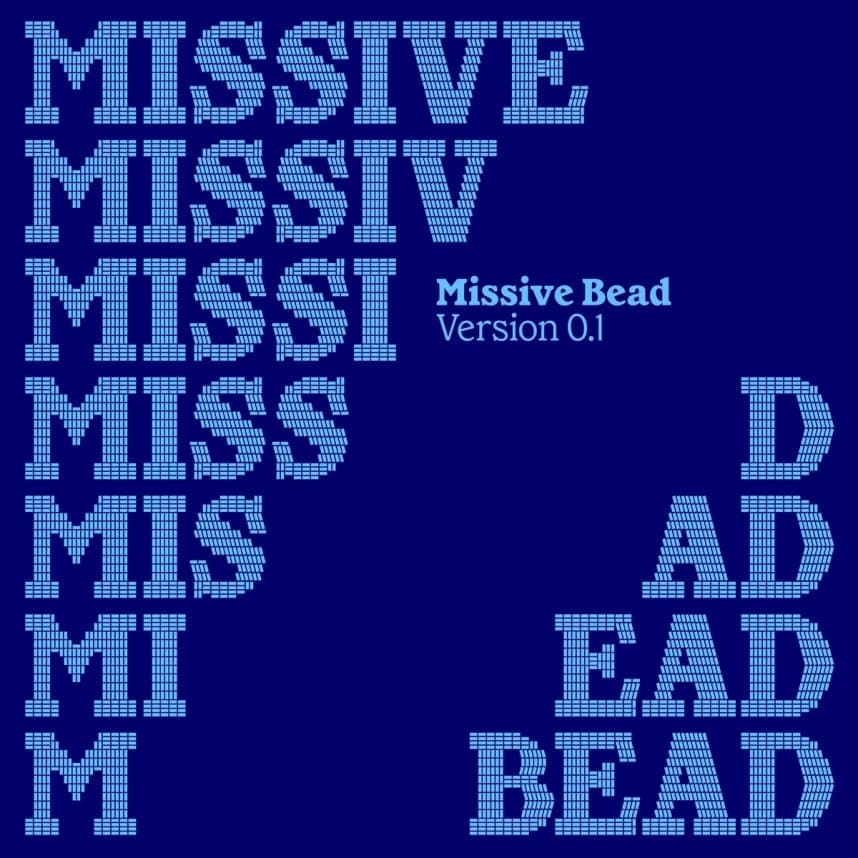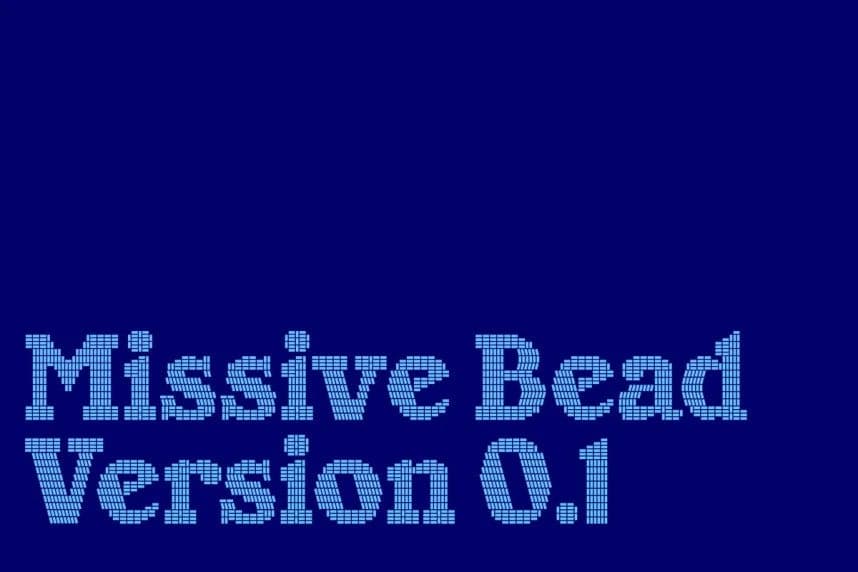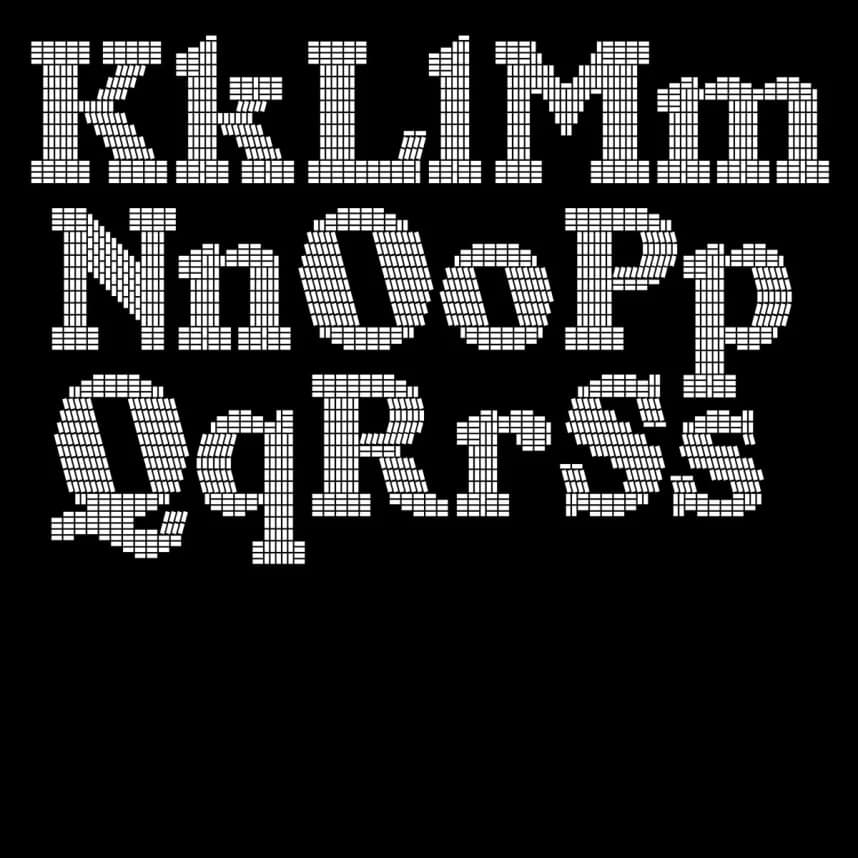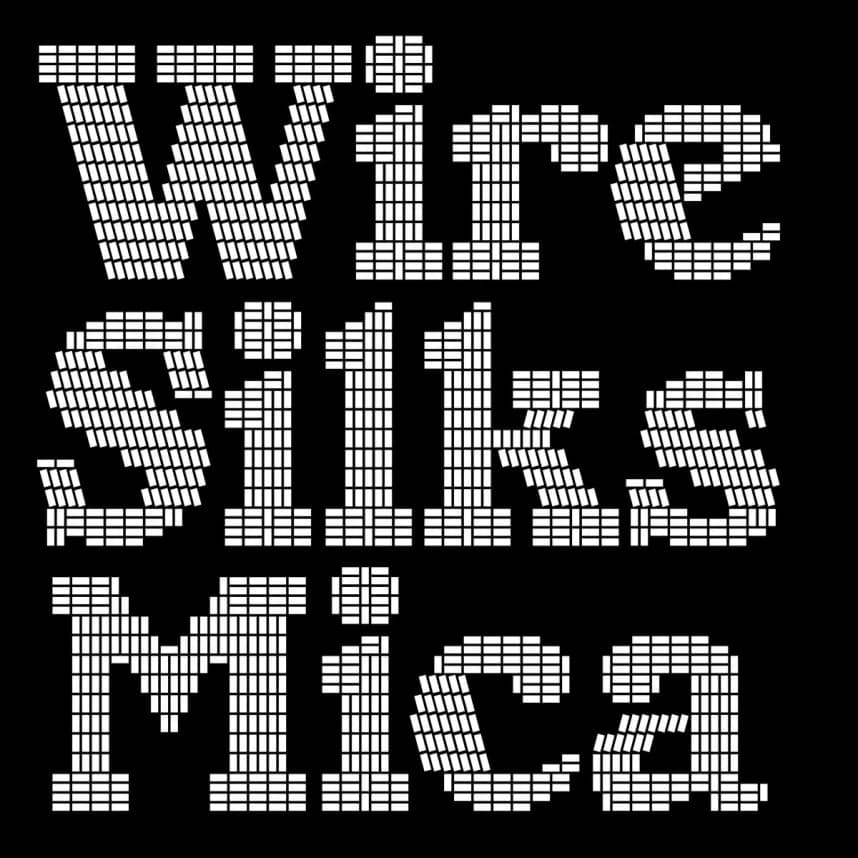
Missive Bead Font, beaded embroidery için okunabilir gösterişli serif biçimlerini sistematik bir dile dönüştürmeyi amaçlayan ızgaraya dayalı bir yazı tipidir. Bir ızgara çerçevesi, genişliğinden daha uzun olan bir tür nakış boncuğu olan “zil boncuğu”nun oranlarını karşılayacak şekilde tasarlandı.
Missive Bead Font, boncuklu nakış için okunabilir gösterişli serif biçimlerini sistematik bir dile indirgemeyi amaçlayan ızgara tabanlı bir yazı tipidir. Bir ızgara çerçevesi, uzunluğu genişliğinden daha uzun olan bir nakış boncuğu türü olan “boru boncuğu”nın oranlarına uyacak şekilde tasarlandı.